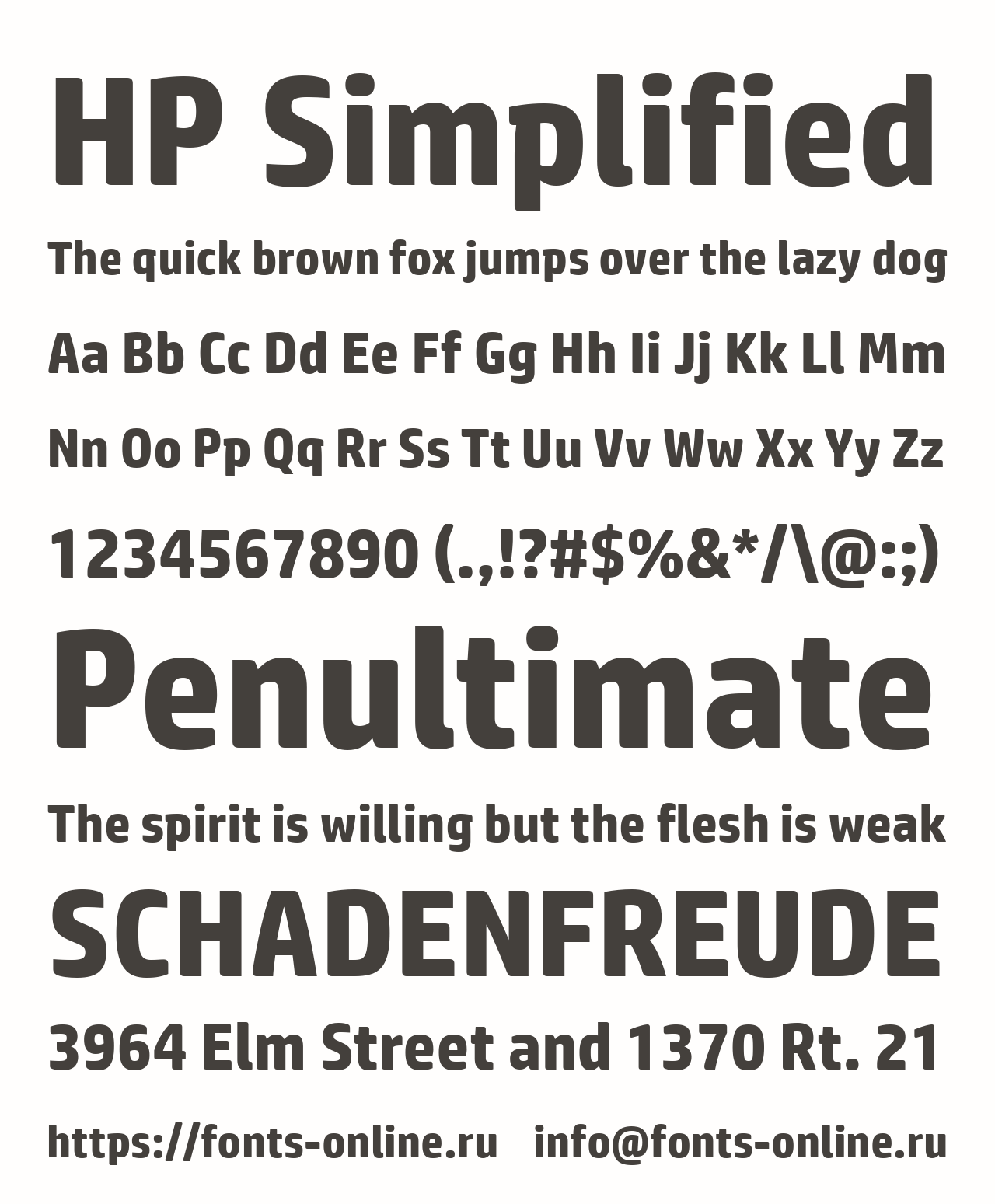
Font HP Việt hóa là gì?
Font HP là hệ thống phông chữ được tối ưu cho các tiêu chuẩn in ấn và hiển thị văn phòng chuyên nghiệp tại Việt Nam. Đặc trưng là cấu trúc nét chữ vững chãi, rõ ràng và có độ tương thích cực cao với các phần mềm đồ họa lẫn ứng dụng văn phòng. Bộ font HP gồm đa dạng các kiểu dáng từ Sans-serif hiện đại đến Serif trang trọng, giúp doanh nghiệp dễ dàng đồng bộ bộ nhận diện từ văn bản hành chính đến tem nhãn sản phẩm.
Việc tìm kiếm bản HP Việt hóa chuẩn Unicode thường khó khăn, dẫn đến lỗi gõ tiếng Việt trên các phần mềm đời mới. In Viva đã tuyển chọn và xử lý kỹ thuật trọn bộ font HP Việt hóa, đảm bảo các ký tự có dấu không bị biến dạng. Nhờ vậy, designer tự tin ứng dụng vào các mẫu túi giấy, hộp giấy mà không lo lỗi hiển thị.
Lưu ý: Khi dùng font HP cho các thiết kế in ấn trên giấy Ivory, bạn nên kiểm tra kỹ khoảng cách các chữ có dấu để bản in trông thoáng đạt và dễ đọc hơn.
Ứng dụng font HP Việt hóa trong thiết kế và in ấn
Nhờ tính ứng dụng cao, phông HP xuất hiện phổ biến trên nhiều ấn phẩm cho doanh nghiệp:
- Thiết kế hồ sơ năng lực công ty: Giúp thông tin hiển thị minh bạch, tạo niềm tin về sự chỉn chu đối với đối tác chiến lược.
- Sản xuất túi giấy đựng tài liệu: Font chữ này thường được dùng cho các thông tin địa chỉ in trên túi Kraft hoặc Ivory vô cùng chuyên nghiệp.
- In ấn sản phẩm cho khối văn phòng: Logo dùng font HP in UV lên bình giữ nhiệt hoặc sổ tay da tạo nên phong cách tối giản và bền bỉ.
- Gia công tem nhãn decal sản phẩm: Giúp các thông số kỹ thuật trên vỏ hộp giấy trở nên dễ đọc, mang lại sự tiện lợi cho người dùng.
Sử dụng font chữ HP cần lưu ý gì?
Để thành phẩm in ấn đạt độ hoàn hảo, designer cần nắm rõ các kỹ thuật sau:
- Lựa chọn độ dày phù hợp: Font HP có đầy đủ từ Light đến Bold. Bạn nên chọn nét Bold cho tiêu đề để tạo sự nổi bật trên hộp quà.
- Tránh dùng cỡ chữ quá nhỏ: Khi in trên giấy nhám, hãy giữ cỡ chữ HP tối thiểu 7pt để tránh tình trạng mực bị lem làm mất nét chữ.